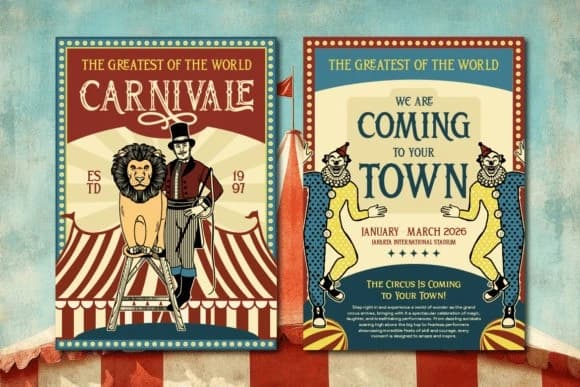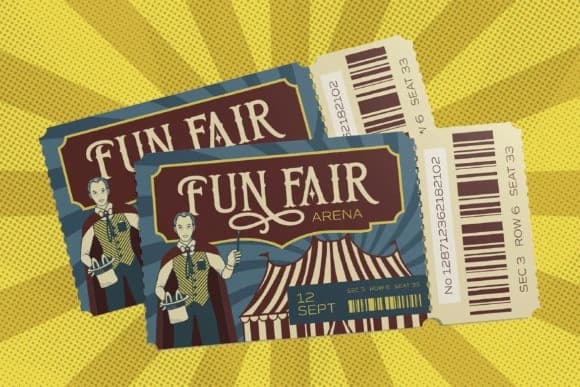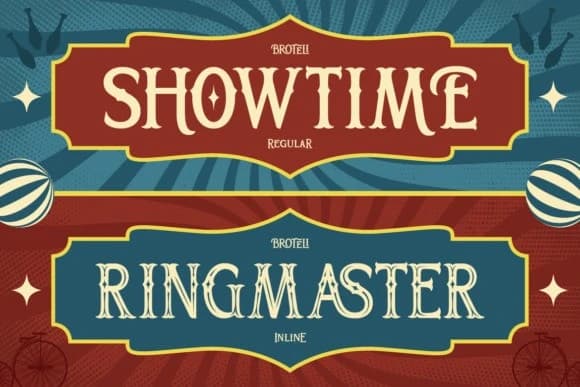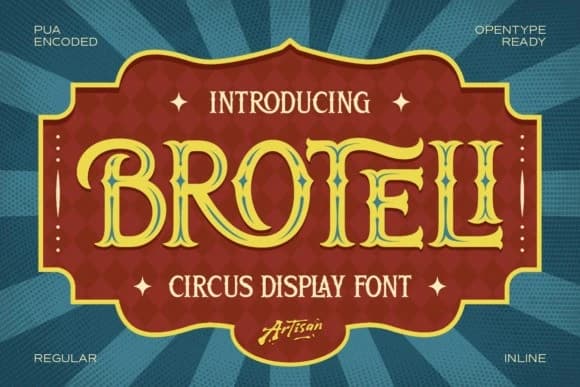
Broteli Vintage Font, klasik karnaval afişlerinden, retro tabelalardan ve eski usul gösteri estetiğinden ilham alan cesur bir vintage gösteri yazı tipidir. Dekoratif serif stiline, oyunbaz kıvrımlara ve güçlü bir kişiliğe sahiptir.
Broteli Vintage Font, klasik karnaval afişlerinden, retro tabelalardan ve eski moda gösteri estetiğinden ilham alan cesur bir vintage gösteri yazı tipidir. Dekoratif serif stiline sahip, eğlenceli kıvrımlara ve güçlü bir kişiliğe sahiptir.